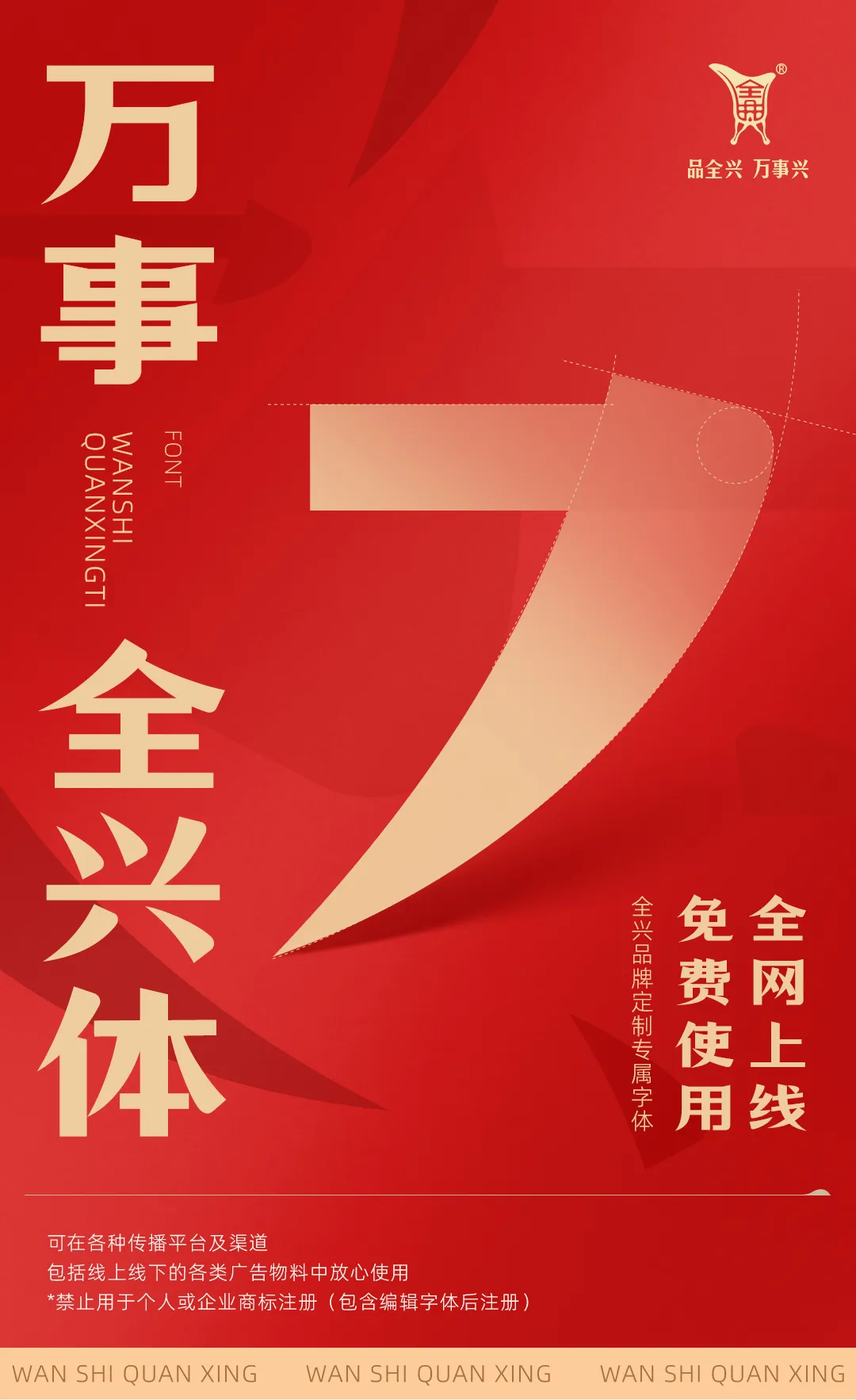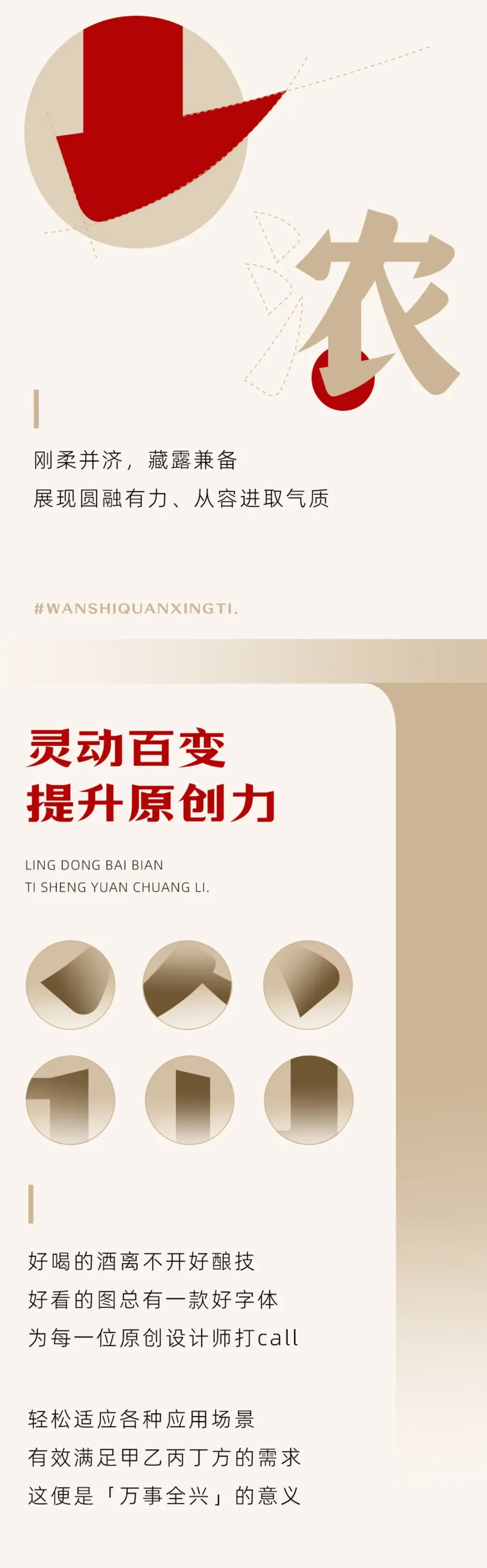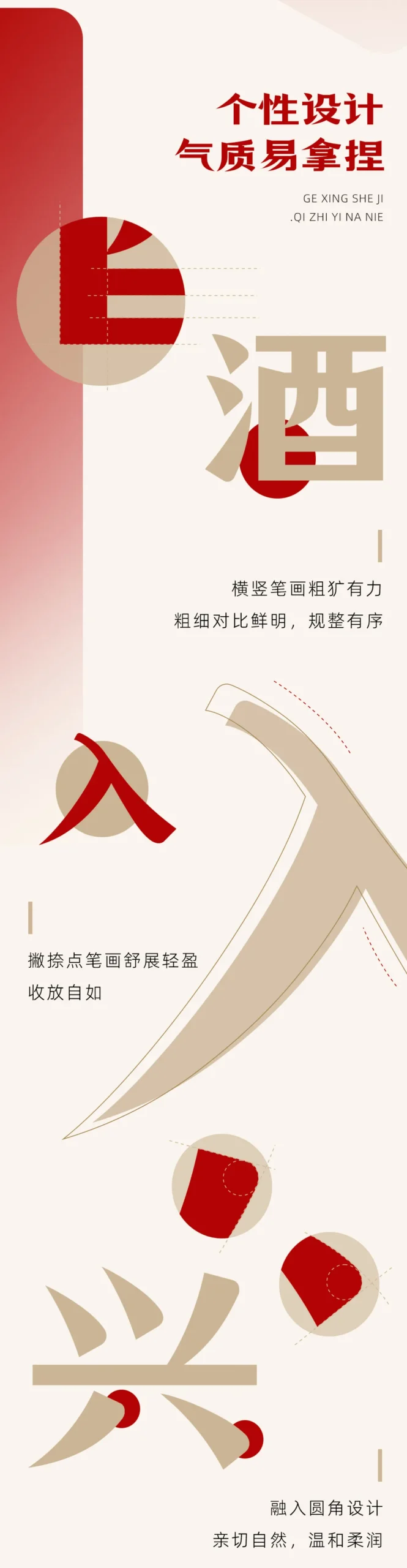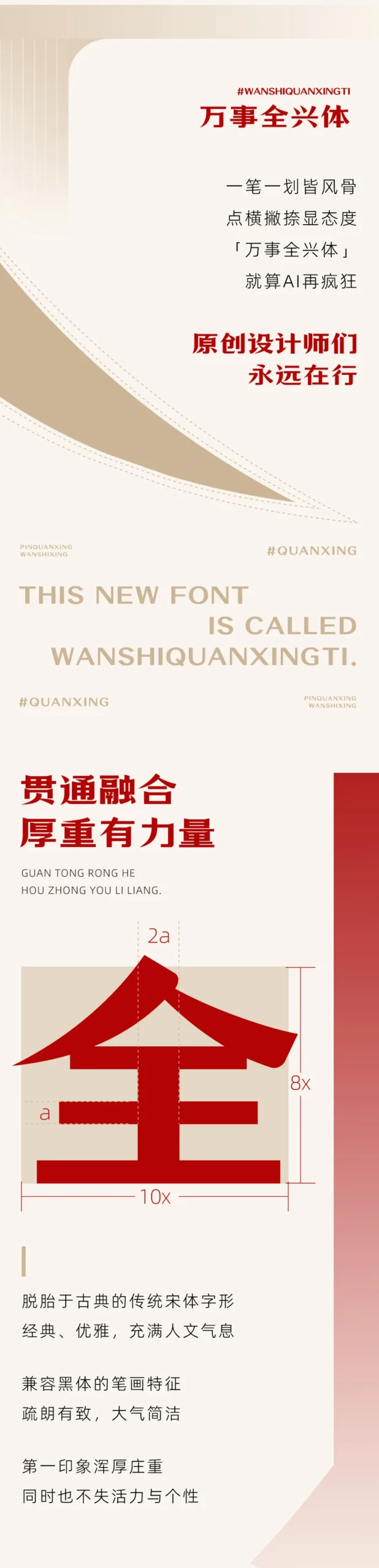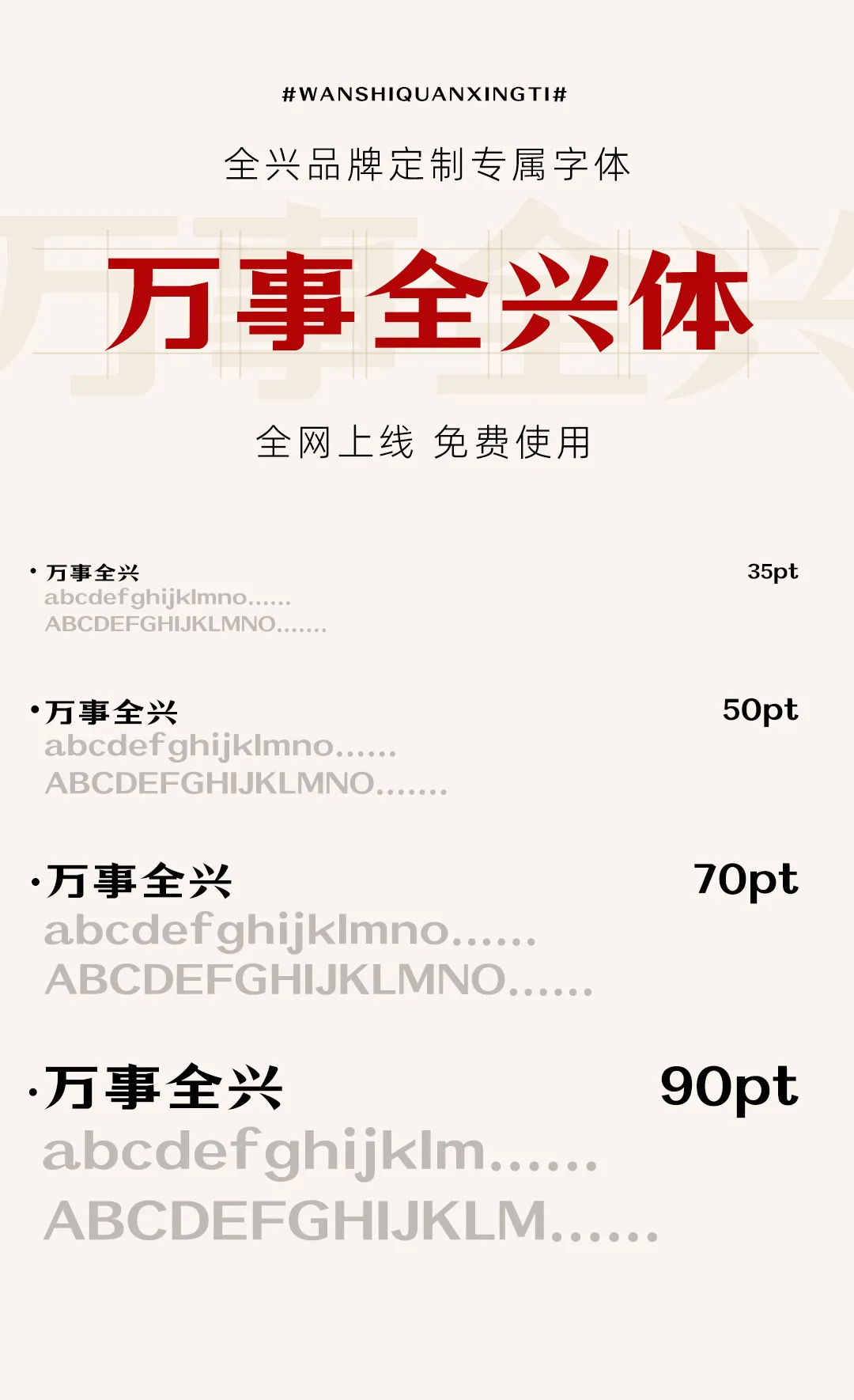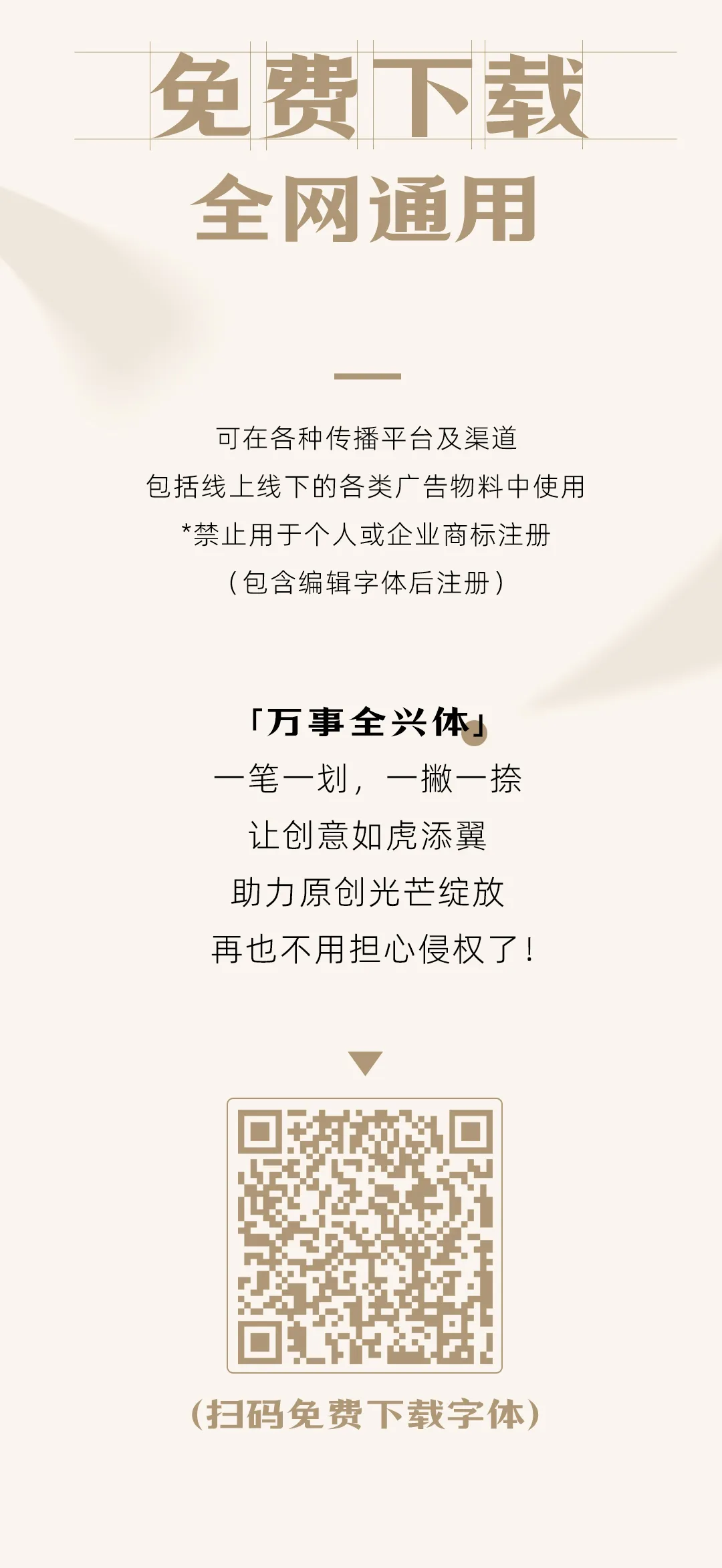
万事全兴体脱胎于古典的传统宋体字形经典、优雅,充满人文气息兼容黑体的笔画特征疏朗有致,大气简洁第一印象浑厚庄重同时也不失活力与个性授权横竖笔画粗犷有力粗细对比鲜明,规整有序撇捺点笔画舒展轻盈收放自如融入圆角设计亲切自然,温和柔润刚柔并济,藏露兼备展现圆融有力、从容进取气质好喝的酒离不开好酿技好看的图总有一款好字体为每一位原创设计师打call轻松适应各种应用场景有效满足甲乙丙丁方的需求这便是「万事全兴」的意义可在各种传播平台及渠道包括线上线下的各类广告物料中使用*禁止用于个人或企业商标注册(包含编辑字体后注册)「万事全兴体」一笔一划,一撇一捺让创意如虎添翼助力原创光芒绽放再也不用担心侵权了!
红色背景海报宣传“万事全兴体”字体全网上线免费使用,适用于各类广告物料,禁止用于商标注册。-刊刻Kntuk
全兴品牌定制专属字体万事全兴体全网上线免费使用,展示35pt至90pt的中英文字体效果-刊刻Kntuk
万事全兴体字体海报,展示汉字“全”的结构比例,说明其脱胎宋体兼容黑体,贯通厚重,经典优雅大气简洁-刊刻Kntuk
个性设计气质易拿捏,酒字横竖笔画粗犷有力,入字撇捺舒展轻盈,兴字融入圆角设计,亲切自然温和柔润。-刊刻Kntuk
“万事全兴”字体宣传海报,主打灵动百变提升原创力,风格刚柔并济,轻松适应各种设计场景,满足多方需求-刊刻Kntuk
免费下载全网通用的万事全兴体字体,可用于各类广告物料,禁止用于商标注册,扫码免费下载字体-刊刻Kntuk